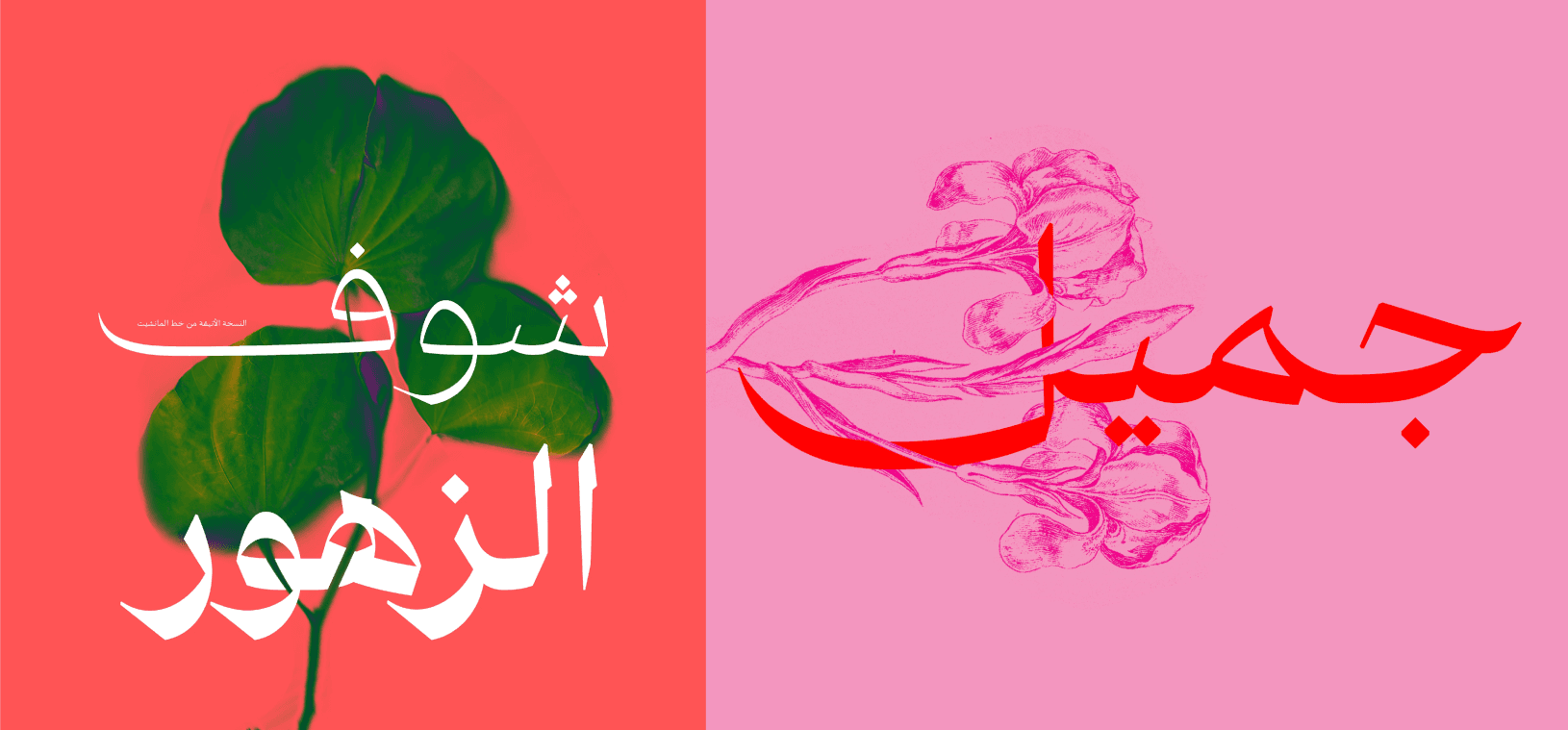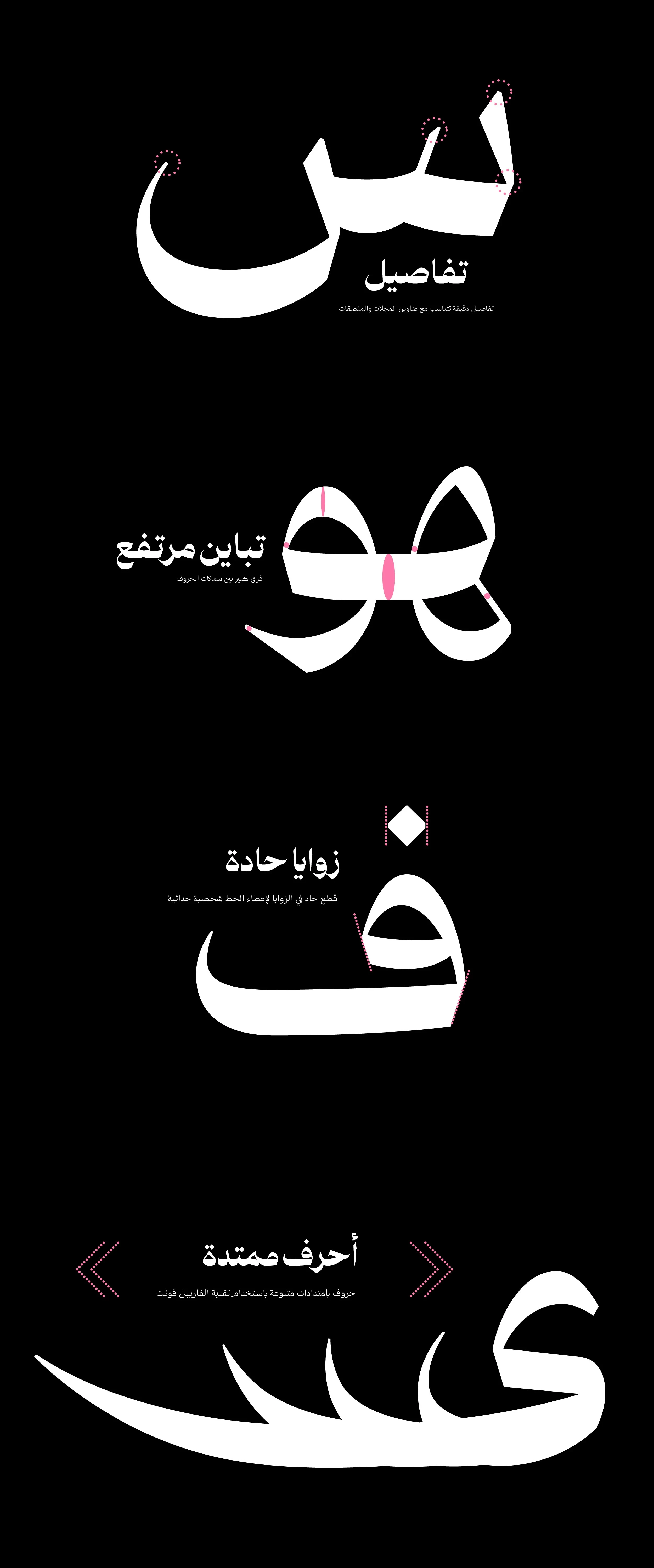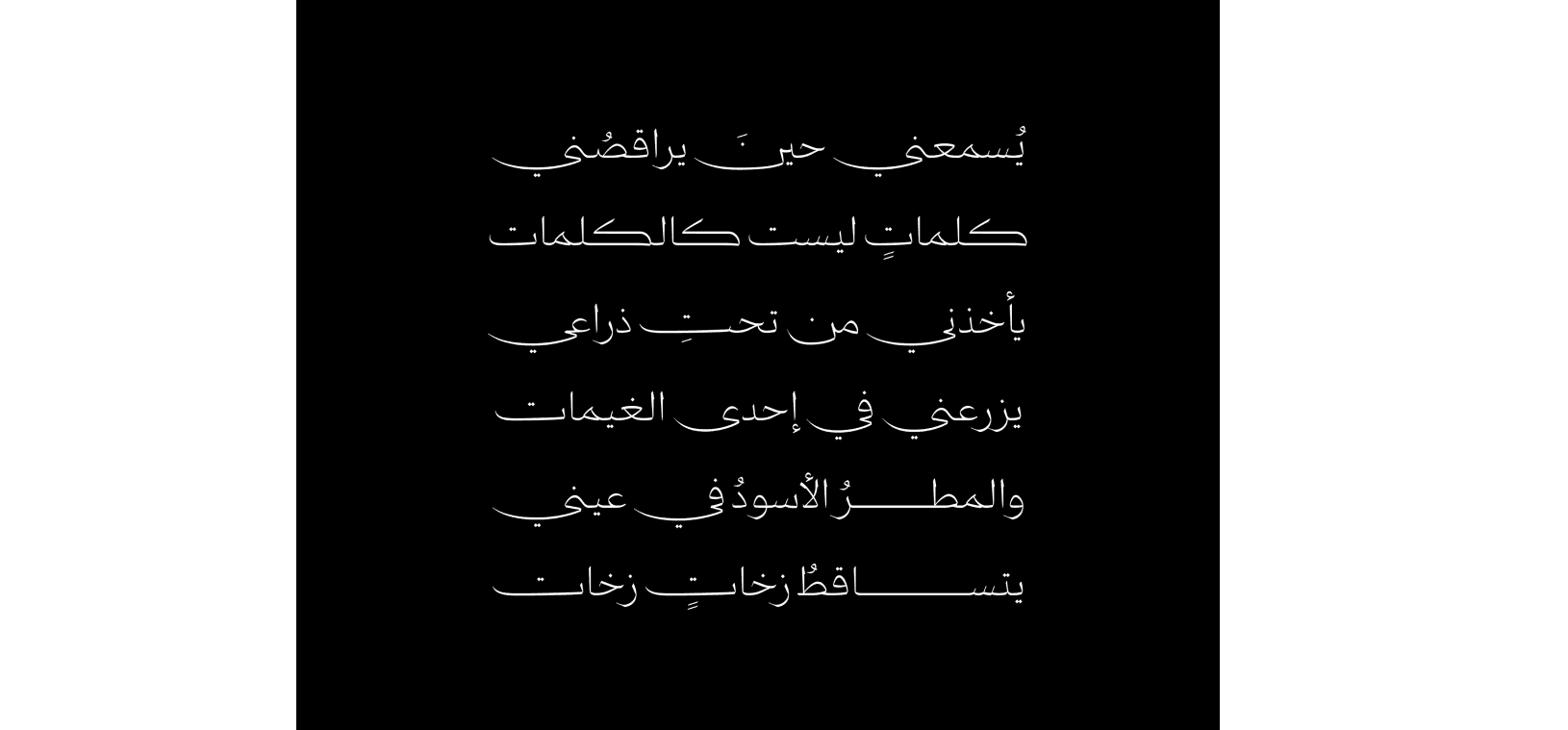
الخط مانشيت Manchit ، من خطوط سلطان مخصص للعناوين الرئيسة في الصحف والمجلات واللافتات الاعلانية واغلفة الكتب وصفحات الويب .
الخط مانشيت يحتوي على اسلوبين (عادي وعريض)